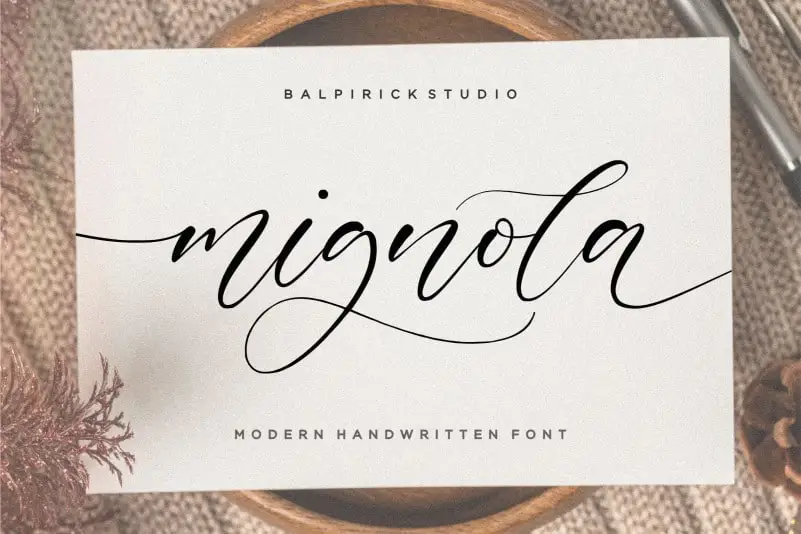
Mignola Calligraphy Font – Download Grátis
A Mignola é uma fonte script perfeita para qualquer projeto criativo no Brasil. Ela se adapta à medida certa para criar design impecável para embalagens de produtos, criação de marcas e projetos de revistas brasileiras. Seja para textos em redes sociais, projetos de casamentos ou apenas para expressar frases acima do fundo, a Mignola tem o poder de torná-los ainda mais interessantes e únicos. Essa fonte foi criada por balpirick e se destaca como uma opção versátil que atende às necessidades dos designers brasileiros em projetos variados. A Mignola traz ao seu design a personalidade e elegância necessária para destacar qualquer projeto, tornando-a uma escolha ótima para quem busca um diferencial único no mercado.